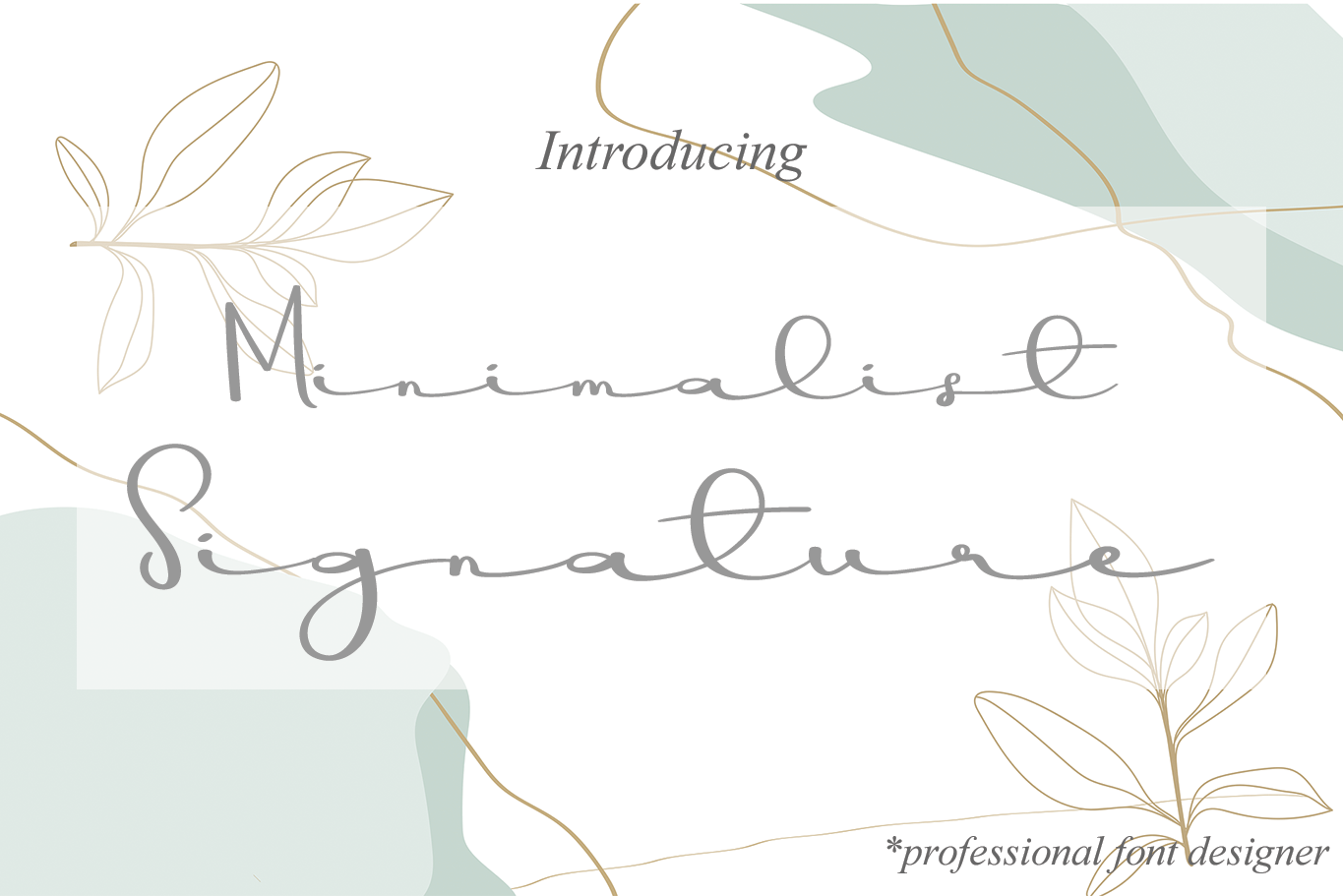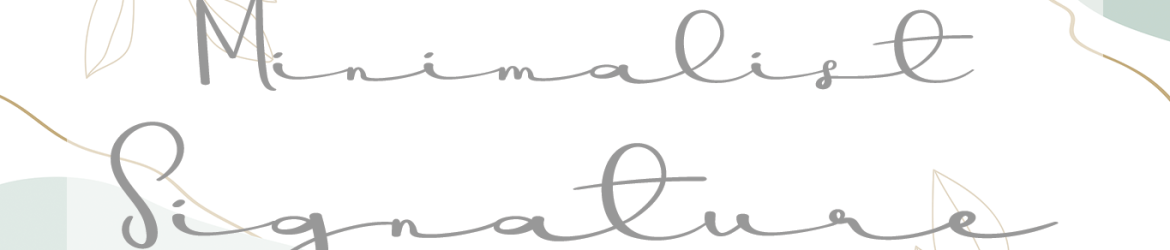
Minimalist Signature Font – Download Grátis
Esta é uma linda e refinada fonte de escrita fechada. Ela tem um visual sofisticado, elegante e moderno, ideal para uso em logomarcas, identidades visuais, convites, material de escritório, designs de casamentos, postagens nas redes sociais e muito mais! Seja você designer ou tipógrafo, essa fonte é perfeita para criar elementos gráficos com um toque sofisticado e moderno. Ela traz uma sensação de classe às suas criações, tornando-a uma escolha ótima para qualquer projeto que exija elegância contemporânea.